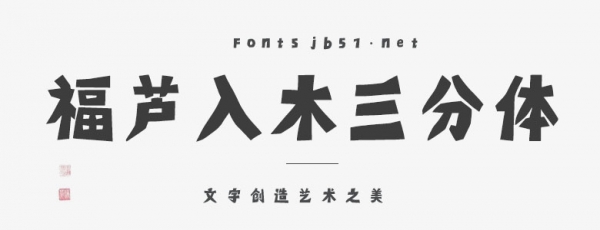
深度提煉中國傳統(tǒng)木版年畫的木刻藝術(shù)內(nèi)核,以刀刻質(zhì)感為視覺語言核心。通過模擬刻刀在木頭上雕琢的動態(tài)過程,在筆畫間塑造自然的頓挫、粗細(xì)變化,還原刻刀入木時“刀走紋理”的真實(shí)痕跡;強(qiáng)化手工雕刻的獨(dú)特肌理,保留筆觸毛邊與刻痕的不規(guī)則感,讓每一處細(xì)節(jié)都流露手工創(chuàng)作的溫度。摒棄機(jī)械美學(xué)的規(guī)整,重現(xiàn)木刻藝術(shù)的技法精髓,傳遞匠人以刀為筆的創(chuàng)作匠心。